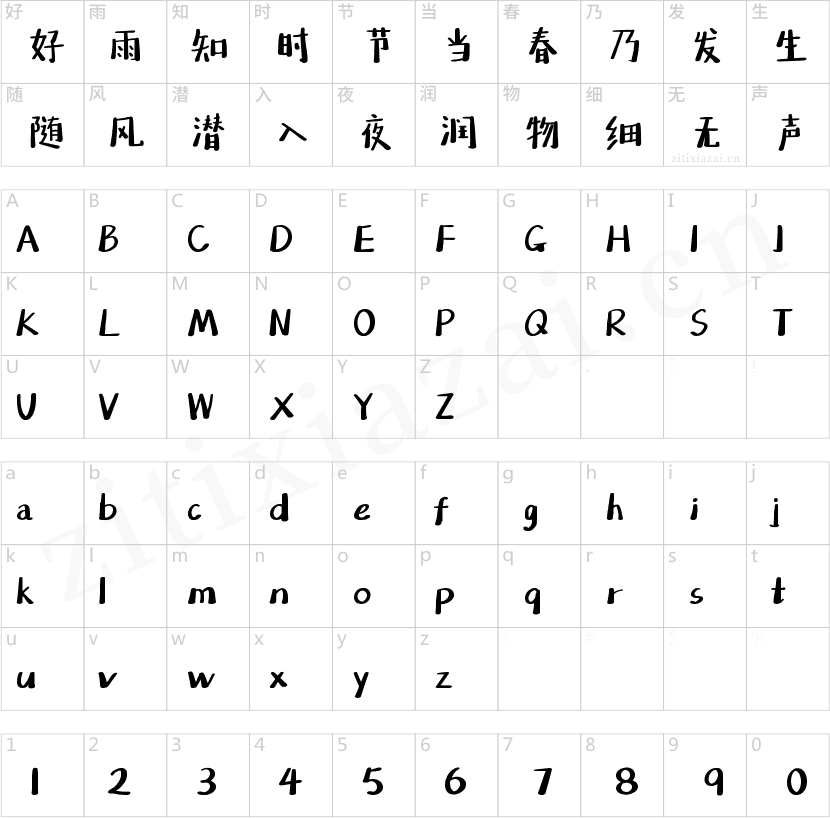
字魂195号-萌趣百奇体
字魂195号-萌趣百奇体,这款字体结构工整、笔画清晰,兼顾美观与易读性,适用于标题、正文、海报、包装、LOGO 等多种场景。字形优雅稳定,风格百搭耐看,适配日常排版与创意设计,让文字呈现更舒适、更具质感。字魂195号-萌趣百奇体一笔一画,皆是细节,以均衡的比例、流畅的线条打造舒适视觉体验,字形端正大气,风格简约现代。无论是商业设计、品牌宣传还是日常排版,都能轻松驾驭,让文字更有格调与力量。字魂195号-萌趣百奇体字体下载。
字魂字体字小魂萌趣百奇体字体是由字魂创意字库设计并生产的一款可商用的字体,被收录于字小魂系列。该字体支持GB-2312标准,包含9170个中文、字母、符号和数字,字体类型偏向硬笔手写,具有可爱、圆润的风格,在市面上广泛用于电商、旅游、印刷品&包装等场景。